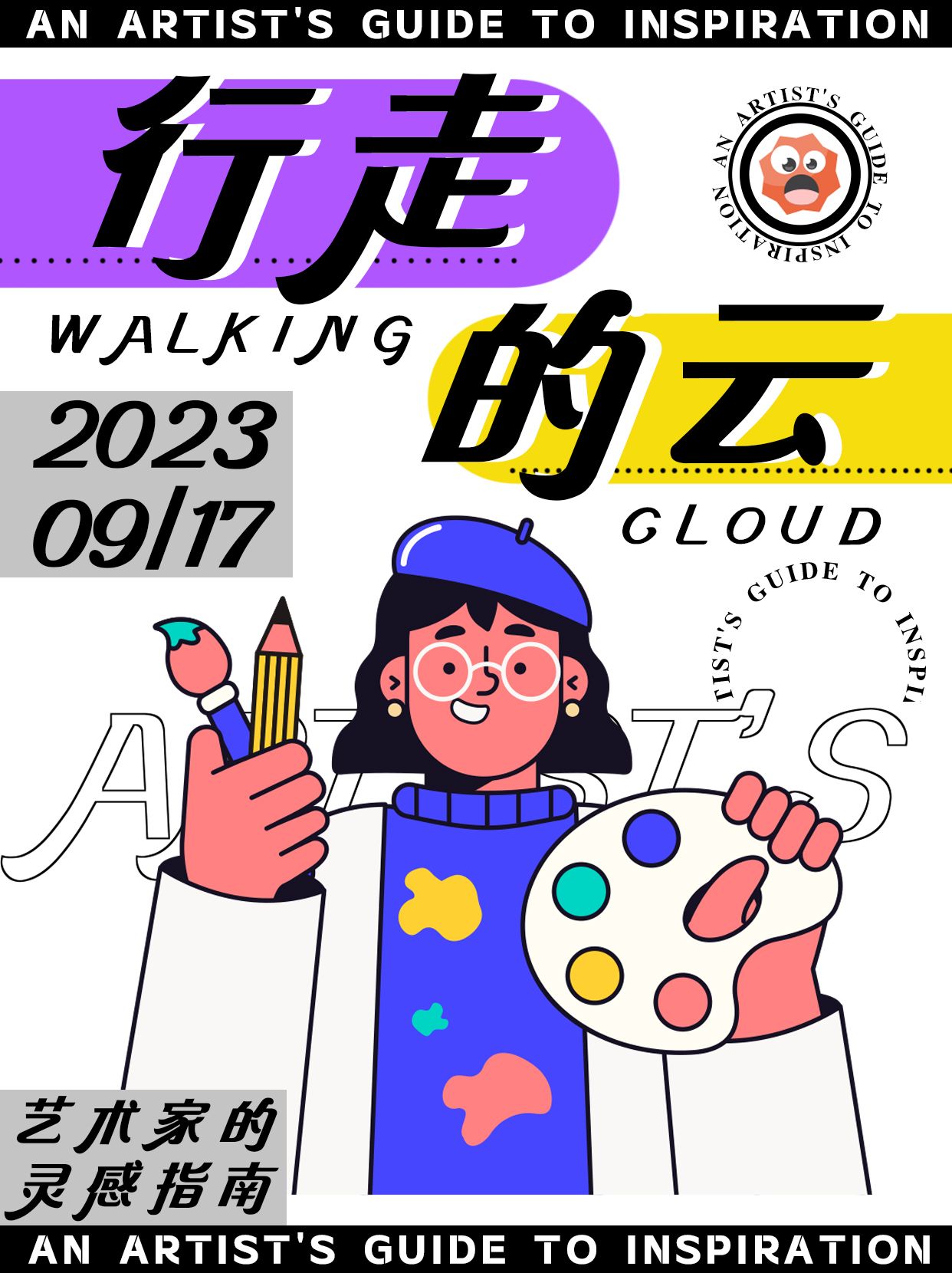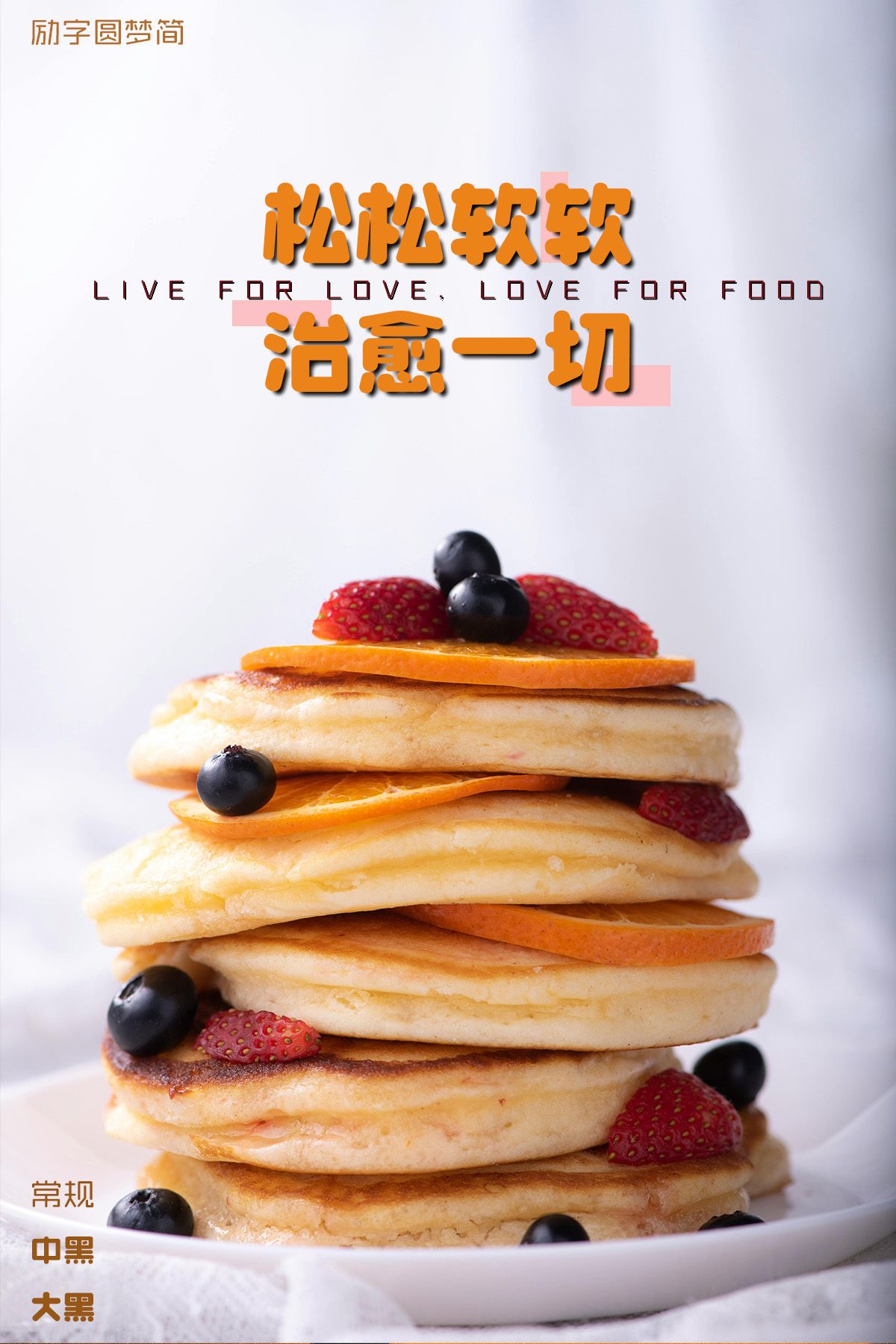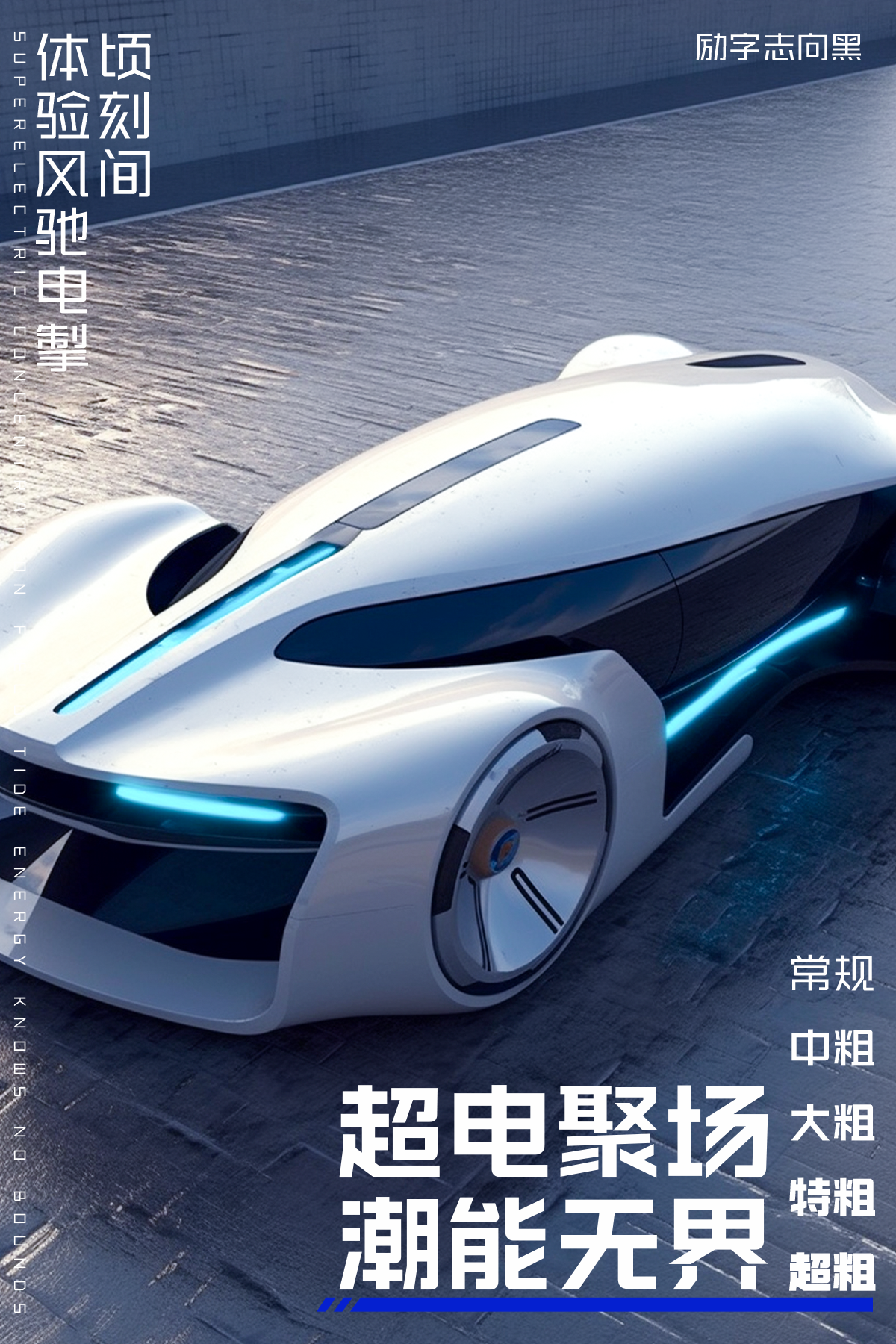
产品包装字体推荐:让产品更有竞争力
在产品包装设计中,字体的选择是至关重要的一环。它不仅关乎产品的外在形象,更承载着品牌故事和产品信息的传递。一个合适的字体与设计融合,能够迅速抓住消费者的眼球,引起共鸣,从而增加产品的吸引力。以下是几款精选的产品包装字体推荐,希望能为您的设计提供灵感。
励字开拓者简 特黑设计独特,笔画线条流畅而富有力量感,能完美体现产品的专业与高端。其深邃的字重,不仅突出了品牌的稳重与大气,更在细节中展现出独特的艺术魅力,让您的产品在众多竞品中脱颖而出,成为消费者的首选。
为产品包装注入活力与创意,我们推荐采用造字侠郝刚快乐简微黑。这款字体设计简洁而不失活力,线条微黑而富有张力,能够迅速吸引消费者的目光。它不仅能凸显产品的独特个性,还能传递出品牌的快乐与活力。选择造字侠郝刚快乐简微黑,能让您对消费者审美需求的精准把握。
当追求品质与力量成为产品包装的关键,励字志向黑简 中粗无疑是最佳选择。这款字体以其独特的黑简风格,展现了品牌的坚韧与决心。励字志向黑简 中粗简洁而不失力量,为产品包装增添了独特的魅力。选择励字志向黑简 中粗字体,不仅彰显了产品的卓越品质,更传递了品牌对消费者的承诺与信赖。
在产品包装设计中,励字圆梦简 大黑以其独特的可爱风格和清晰的视觉效果,为产品增添了一份别样的魅力。这款字体线条流畅,形态圆润,给人一种亲切、温馨的感觉,非常适合用于儿童或女性产品的包装内。选择励字圆梦简 大黑,不仅能让产品包装更加吸引人,还能在无形中拉近品牌与消费者之间的距离,提升产品的市场竞争力。
总之,合适的字体选择对于产品包装至关重要。通过精心挑选和设计字体,不仅能够提升产品的美观度,还能更好地传递品牌信息和产品价值,吸引更多消费者的关注和喜爱。